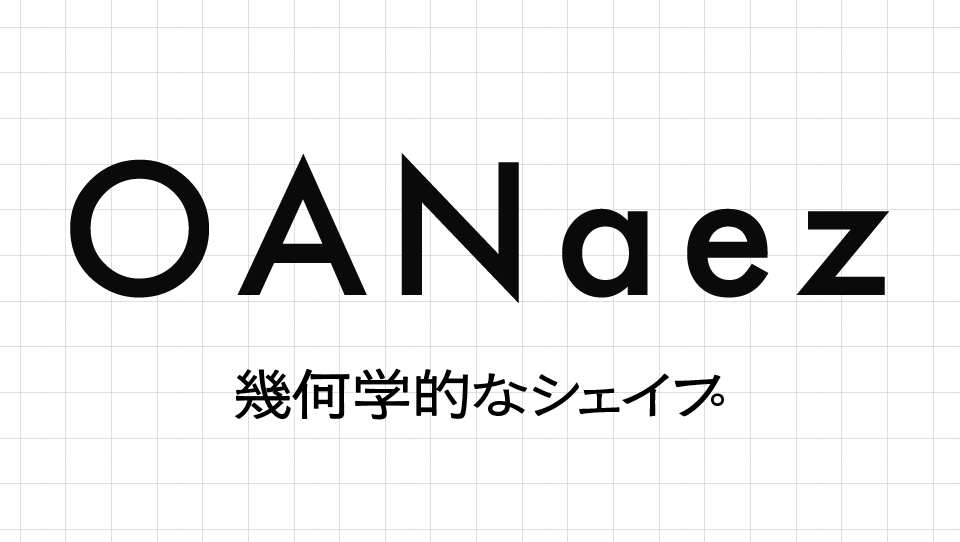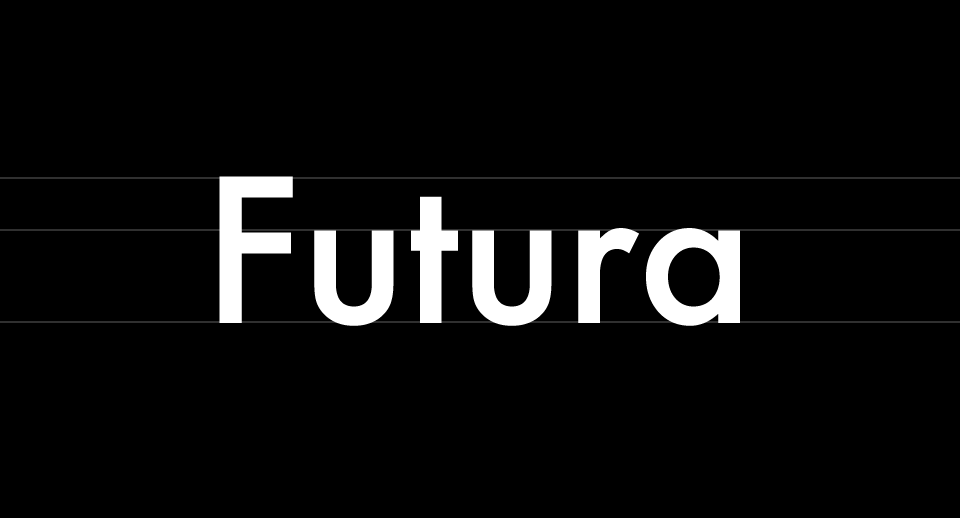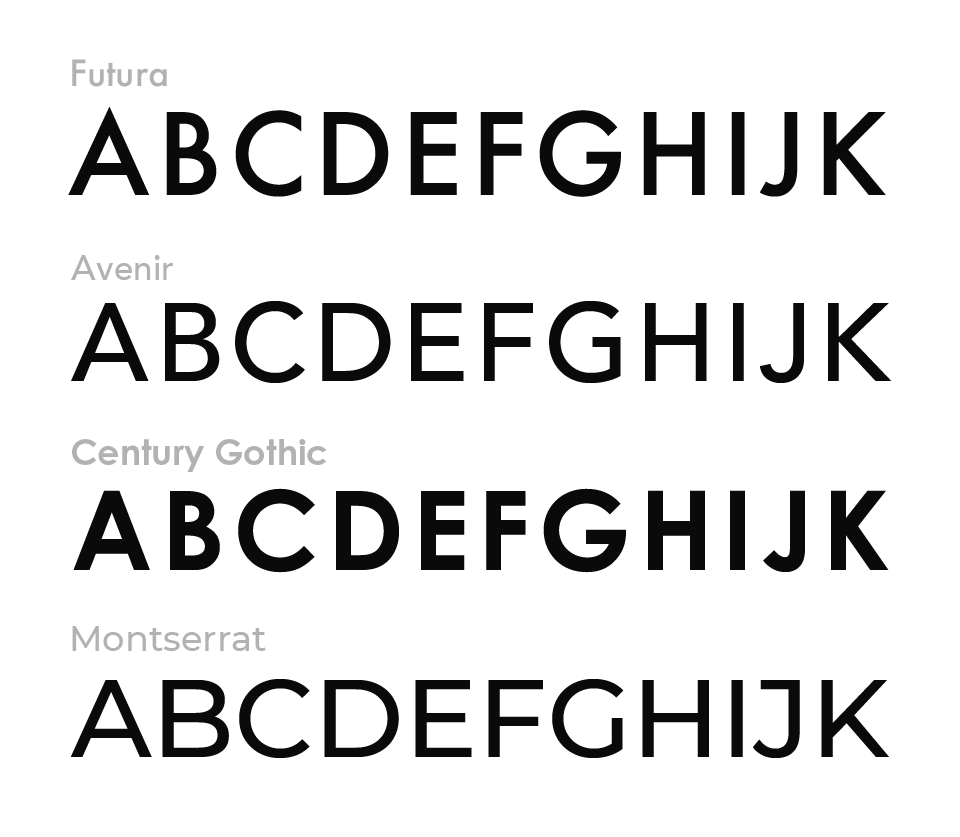
「Futura(フツラ・フーツラ)」の魅力とは?幾何学的で未来的なデザインが愛され続ける理由
シャープで端正、それでいてどこか未来的な印象を与えるフォント「Futura(フツラ・フーツラ)」。
名前の通り“未来”を感じさせるこの書体は、バウハウス思想を色濃く受け継ぎ、20世紀初頭に登場して以来、時代を超えて多くのデザインシーンで活躍してきました。ポスター、ロゴ、広告、映画タイトル……Futuraの活躍の場は実に多彩です。
この記事では、Futuraの誕生背景からデザイン的な特徴、類似フォント、企業での活用事例、さらにはカルチャーに与えた影響まで、あらためてその魅力を掘り下げていきます。
Futura(フツラ・フーツラ)とは
Futuraは、1927年にドイツのタイポグラファー、パウル・レナー(Paul Renner)によってデザインされたサンセリフ体フォントです。
その名前が示すとおり、「未来的(Futuristic)」な印象を持たせる目的で設計されており、当時としては非常にモダンで革新的なフォントでした。
当時はバウハウス運動の影響が強く、合理性や機能美を追求するデザインが流行していました。Futuraは、そうした時代背景の中で生まれた、まさにバウハウス的思想を体現するフォントと言えます。
バウハウスとは、1919年にドイツで設立された美術・建築・デザインの総合学校です。創設者のヴァルター・グロピウスは、芸術と工業技術の融合を目指し、「機能的で美しいデザイン」を追求しました。
バウハウスの理念は「形は機能に従う」という考え方に基づき、無駄を省いたシンプルで実用的なデザインを重視していました。1933年にナチスによって閉校されるまでの短い期間でしたが、その影響は現代の建築・プロダクトデザイン・グラフィックデザインの基礎を築き、今日まで大きな影響を与え続けています。
Futura(フツラ・フーツラ)の歴史
Futuraは、1920年代後半にドイツのバウハウス思想と共鳴しながら開発されました。パウル・レナー自身はバウハウスの正式なメンバーではなかったものの、そのデザイン哲学を深く理解しており、「装飾を排し、機能に従う」美学を文字デザインに落とし込みました。
Futuraは、発売後すぐに世界中で高く評価され、20世紀のモダニズムデザインに欠かせないフォントとして定着しました。特に印刷媒体やポスター、建築のサインなどで多く使用され、デジタルフォントとしての再評価も進み、現在でも根強い人気を保ち続けています。
Futura(フツラ・フーツラ)の特徴
Futuraの最大の特徴は、幾何学的なシェイプにあります。円や直線、正三角形といった基本図形をもとに設計されており、特に「O」や「a」などの文字にはその美しさが如実に表れています。
また、xハイトが低めで、縦長でシャープな印象を与える字形が多く、スピード感や未来感を演出するのに適しています。一方で、幾何学形状にこだわるあまり、可読性が犠牲になる場面もあり、小さいサイズや長文では慎重な使い方が求められます。
フォーマルすぎずカジュアルすぎない、絶妙なバランス感覚もFuturaの魅力の一つです。
Futura(フツラ・フーツラ)の類似・代替フォント
Futuraは有料フォントのため、プロジェクトによっては類似のフリーフォントや代替書体を活用する場面もあります。以下はFuturaに近い印象を持つ代表的なフォントです。
どうしても使いたいといったケースでも代替フォントとして類似フォントを使うこともできます。
- Avenir(アヴェニール)
より人間味を加えた設計。可読性が高く、Futuraのモダンさを継承しつつバランスが良い。 - Century Gothic
Windows標準搭載で使いやすく、Futuraに非常に似た幾何学的サンセリフ体。 - Montserrat(Google Fonts)
Google Fontsから使うことができるので、Webフォントとして人気。現代的なトーンでFuturaに通じる印象を持ちつつ、より親しみやすい。 - Josefin Sans(Google Fonts)
こちらもGoogle Fontsから使うことができます。やや装飾的なFutura風で、レトロな雰囲気を加味したい場面に最適。
Futura(フツラ・フーツラ)を使用した企業ロゴ・事例
Futuraは、ブランドイメージに「革新性」「信頼」「幾何学的な洗練」を与えるフォントとして、多くの企業・プロダクトに採用されています。代表的な事例は以下のとおりです
- Volkswagen(フォルクスワーゲン)
長年にわたってFuturaをブランドタイプとして使用。 - Supreme(シュプリーム)
シンプルで強い印象を与えるFutura Boldをベースにしたロゴが印象的。少し斜体をかけて変形しているようです。 - LOUIS VUITTON(ルイ・ヴィトン)
ロゴタイプにFuturaがベースとされています。比較的にそのまま使用しているようです。 - Nike(ナイキ)
一部の広告やプロモーションでFuturaを採用。
これらのブランド事例からも、Futuraが「未来的で信頼性のあるイメージ」を与えるフォントとして使用されていることもわかりますが、スポーティな印象や高級感を感じされるといったユニークなフォントです。
Futuraが使われた映画・書籍・カルチャー
Futuraは映画や書籍でも多く使われており、視覚的なインパクトを求める表現に重宝されています。
- 映画『2001年宇宙の旅』では、ポスターやタイトルにFuturaが使われ、その未来感をさらに際立たせています。
- 映画監督のウェス・アンダーソン作品ではFuturaがたびたび登場し、統一感ある美しい世界観の一端を担っています。
- 書籍やアートブックでも、タイポグラフィにこだわるデザインにおいて頻繁に採用されています。
まとめ
Futuraは、ただ整ったフォントというだけではありません。
直線や円といった幾何学のルールに忠実でありながらも、どこか温度のある、不思議な“ぬくもり”を感じさせてくれるフォントです。無駄を削ぎ落としたミニマルな設計なのに、見た瞬間に強く印象が残る。そんな不思議なバランスが、多くのデザイナーやブランドに選ばれてきた理由なのかもしれません。
時代が進んでも、テクノロジーが進化しても、Futuraの美しさは古びることがありません。むしろ、その整いすぎた美が、いまだからこそ新鮮に映ることもあります。未来を見つめて作られたFuturaは、100年近く経った今も、しっかりと未来を語る力を持ち続けています。デザインの現場において、これほど長く、そして深く愛されているフォントはそう多くありません。
私個人もFuturaが大好きで、よく使ってしまうフォントの1つです。Futuraをまだ使ったことがない方も、ぜひ一度使ってみてください。